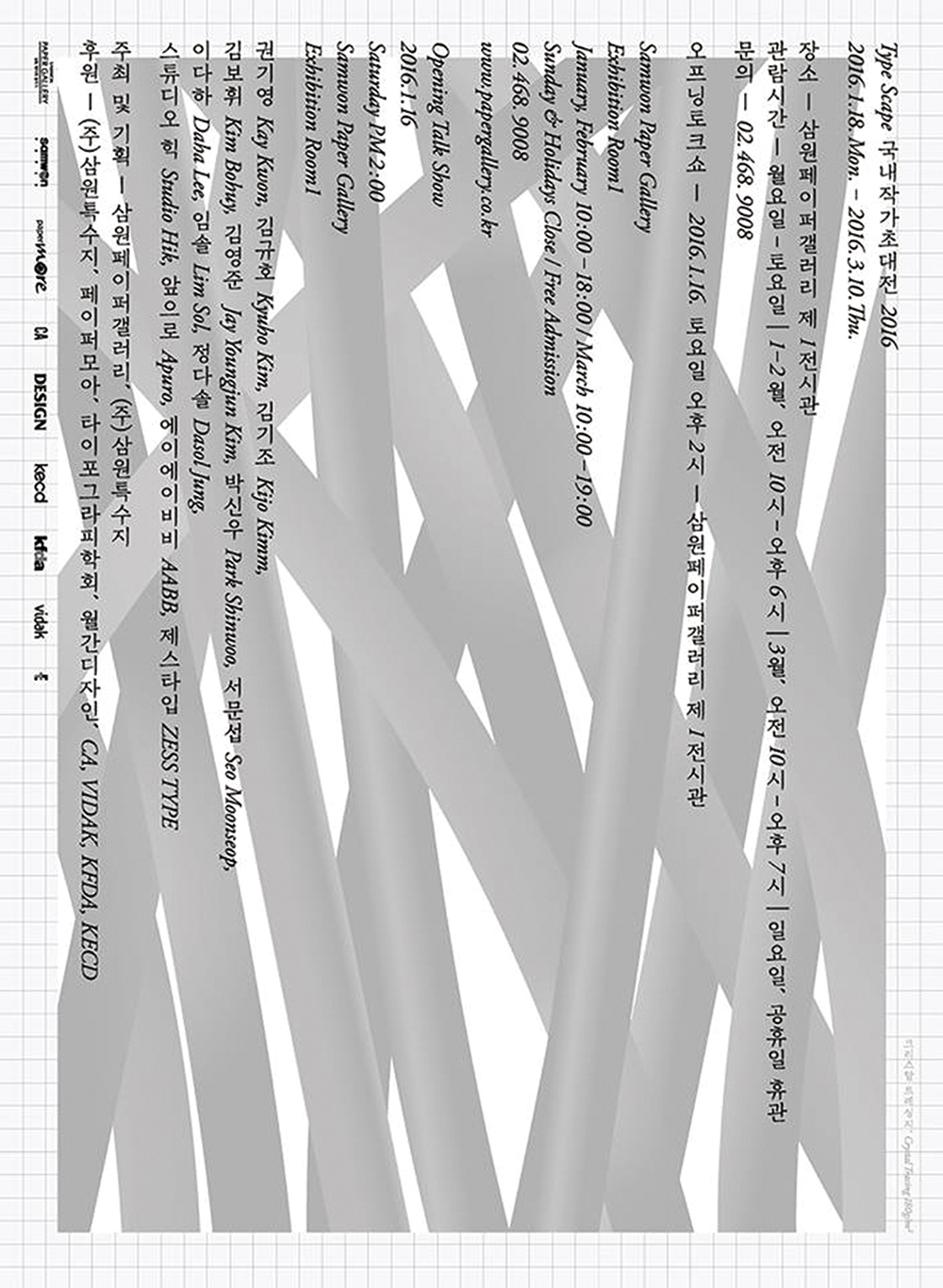
<타입 스케이프> 전시 : 오프닝 토크쇼
지난달 16일, 삼원페이퍼갤러리에서 국내작가 초대전 2016 <타입 스케이프> 오픈에 앞서 토크쇼가 개최되었다. 총 14팀의 참여 작가/스튜디오 중 12팀이 참석하였고, 주제별로 세 개의 그룹으로 나누어 2시간 남짓 타이포그래피와 관련된 대화를 나누었다.
국내 작가 초대전 2016 <타입 스케이프> : 오프닝 토크쇼
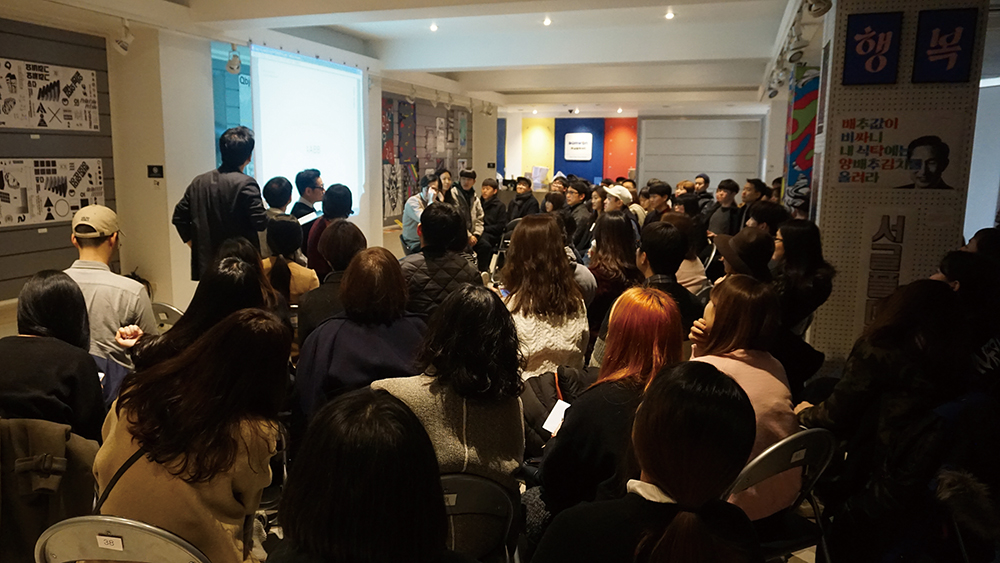
<타입 스케이프> 오프닝 토크쇼 현장
지극히 주관적인: 디자이너가 선호하는 타입페이스
첫 번째 그룹은 ‘디자이너가 선호하는 타입페이스’라는 주제로 권기영, 에이에이비비, 스튜디오 힉, 제스 타입이 대화에 참여했다. 이 그룹에서는 작가들 각각 서체의 어떤 점을 선호하고 불호하는지, 나아가 어떠한 지점에 강조점을 두고 타입 디자인을 진행하는지에 대해 들어볼 수 있었다.
에이에이비비의 석재원은 실제 경험을 토대로 명세서에 사용하고 있는 아쿠라트(Akkurat) 서체에 대해 설명했다. 아쿠라트는 모노 타입과 레귤러 타입으로 구분되는데, 각자의 타입을 용이한 지점에 알맞게 사용하는 것이 이 서체의 가장 큰 특징임을 강조한다. 특히 여전히 계산기를 사용하는 본인의 경우, 본문은 레귤러 타입으로 작성하지만 금액란에는 숫자의 자간이 동일한 모노 타입을 사용하여 세로 계산을 용이하게 한다고 밝혔다.
한편, 에이에이비비의 구자은과 김민재는 각각 미세스 이브스(Mrs. Eaves), 가라몬드 프리미어 프로(Garamond Premier Pro)를 선호하는 서체로 꼽았다. 스튜디오 힉과 권기영은 좋아하는 서체 하나를 꼽는 것은 어려운 일인 데에 생각을 같이 하면서, 스튜디오 힉은 가장 완벽한 서체로 구현된 헬베티카(Helvetica) 이전 서체들의 매력에 대해 어필했다. 또한, 제스 타입은 본문보다는 제목용 글꼴인 헤드라인, 그래픽 글꼴, 장식용 글꼴을 선호한다고 밝히며 선호 글꼴로는 휴먼 엑스포와 울릉도체를 꼽았다.
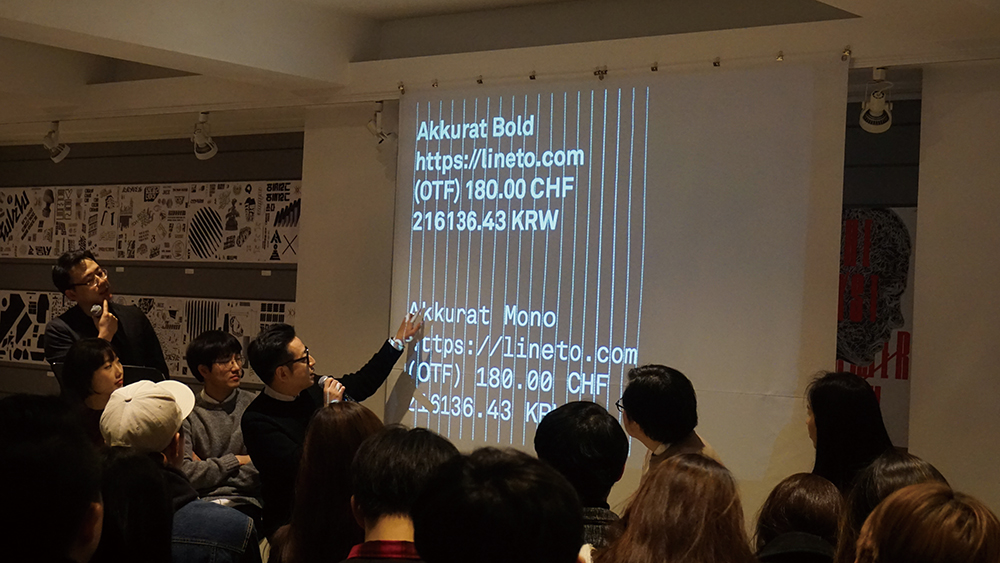
에이에이비비의 석재원이 아쿠라트 서체의 모노 타입을 설명하고 있다
타이포그래피의 고민: 가독성과 심미성
두 번째 그룹은 ‘가독성과 심미성’을 주제로 김기조, 이다하, 박신우, 서문섭이 대화에 참여했다. ‘예쁜데 안 읽혀요’를 해결하면 ‘읽히는데 안 예뻐요’로 순환되는 끝없는 전쟁.
김기조는 네모꼴 정방형에 가득 채워 만드는 본인의 작업을 예시로 들면서, 대체로 획을 굵게 쓰는 편이라 글자가 부딪치는 경우를 방지하고자 일종의 장치들을 삽입한다고 밝혔다. 이를테면 방점을 찍거나 박스, 그루핑(grouping)을 하면서 인위적으로 읽는 방법을 조정하는 것이다. 그는 가독성이 단순히 디자인만의 차원이 아님을 설명하며 일상적인 단어에 한해, ‘ㅡ’와 같은 모음들은 과감히 생략해도 가독성이 떨어지지 않는다는 것을 강조했다. 즉 우리의 문화나 언어 수준에 따라, 익숙한 단어나 눈에 익은 글자들은 모종의 변형이 일어나도 의미 해석이 가능하다는 것이다. 이외에도 김기조는 포인트에 따라 같은 타이포그래피라도 획의 굵기를 조절하여 가독성을 높이는 방식에 관해 설명했다.
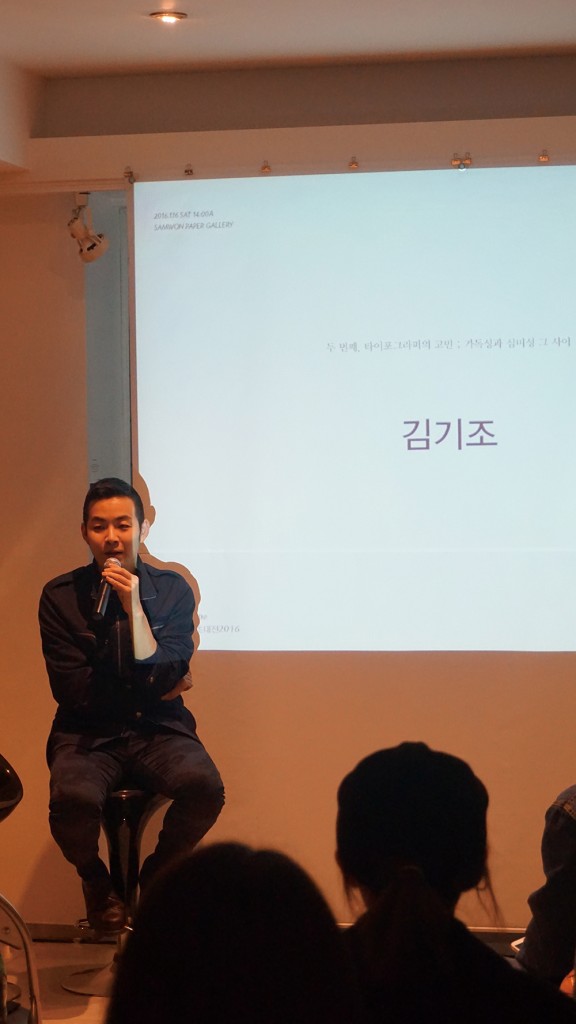
기조측면의 김기조가 가독성과 심미성에 대해 설명하고 있다
타이포그래피가 그래픽 디자인에 미치는 영향
마지막 주제인 ‘타이포그래피가 그래픽 디자인에 미치는 영향’에는 김규호, 김보휘, 앞으로 스튜디오, 임솔이 함께했다.
앞으로 스튜디오는 민음사에서의 편집 디자인 경험을 바탕으로, 책 표지의 탈락한 시안을 보완하는 방식에 대해 설명했다. 대형 출판사에서의 디자인은 ‘잘 팔려야 한다’는 압박과 함께 편집부, 마케팅부 등과의 커뮤니케이션이 활발히 이루어진 후에야 확정이 된다는 특징이 있다. 이러한 지점들 때문에 고사되었던 시안들이 그래픽 디자인의 도움으로 구제 받은 몇 가지 예시를 들어볼 수 있었다. 컨셉은 그대로 유지하되 질감이나 텍스처가 바뀌면 미감이 달라진다는 점을 활용해 일반 재질을 홀로그램으로 변형하기도 하고, 밋밋한 글자를 네온사인 모양으로 바꾸는 등의 시도를 곁들였던 경험을 들려주었다. 한편, 김보휘는 그래픽 디자인과 타이포그래피는 하나라는 점을 강조하며, 영향이란 서로 다른 범주에 있는 것들이 주고받는 것이라고 설명했다.
국내 작가 초대전 2016 <타입 스케이프>
전시 내용: 국내 작가 및 스튜디오의 타입 기반 작품. 14팀 참여, 총 80여 점 전시.
참여 작가: 권기영, 김규호, 김기조, 김보휘, 김영준, 박신우, 서문섭, 이다하, 임솔, 정다솔, 스튜디오 힉(Studio Hik), 앞으로(Apuro), 에이에이비비(AABB), 제스 타입(ZESS TYPE)